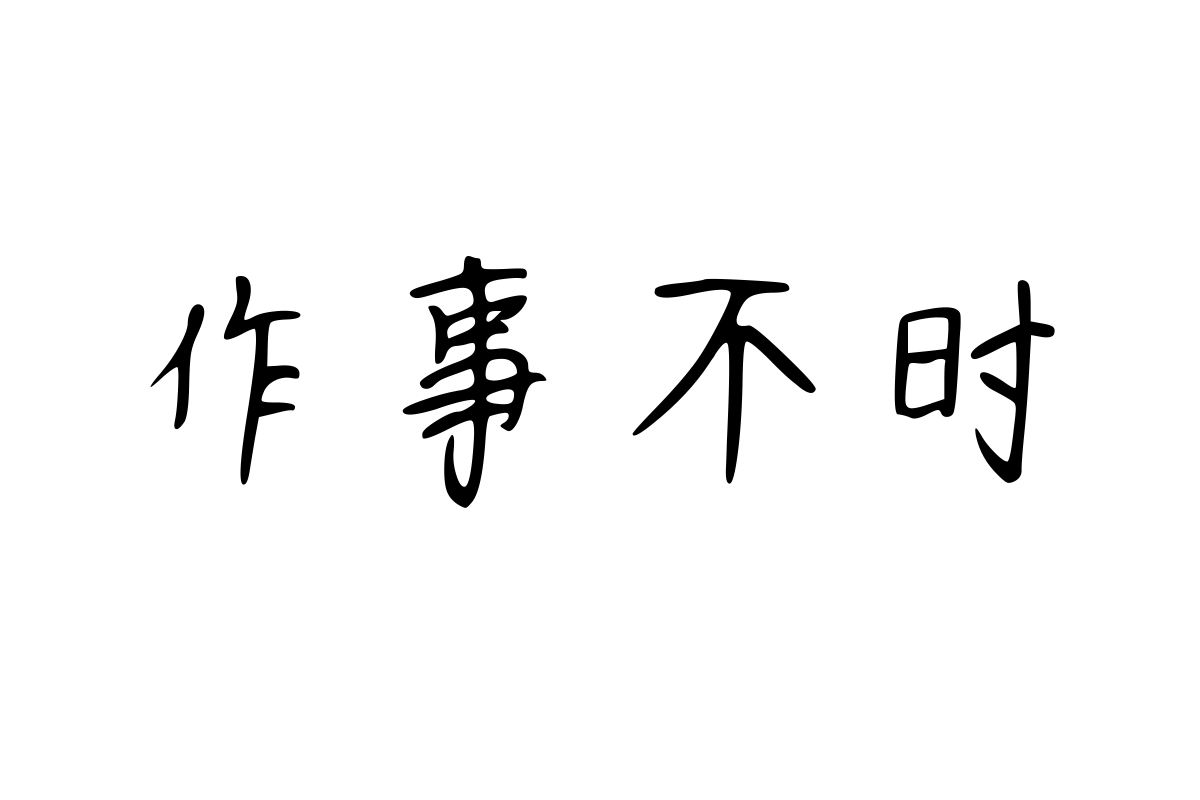
思雨奔二青年是一款具有现代感的中文字体,它以其简洁、明快的特点受到许多设计师和品牌的青睐。这款字体的设计灵感来源于中国的传统书法艺术,但又融入了现代设计元素,使其既具有传统韵味,又不失时尚感。
思雨奔二青年的字形结构紧凑,笔画清晰,线条流畅。它的每个字符都经过精心设计,使得整体看起来既有美感又易于阅读。这款字体适用于各种商业、广告、包装等设计领域,能够很好地传达出品牌的现代感和活力。